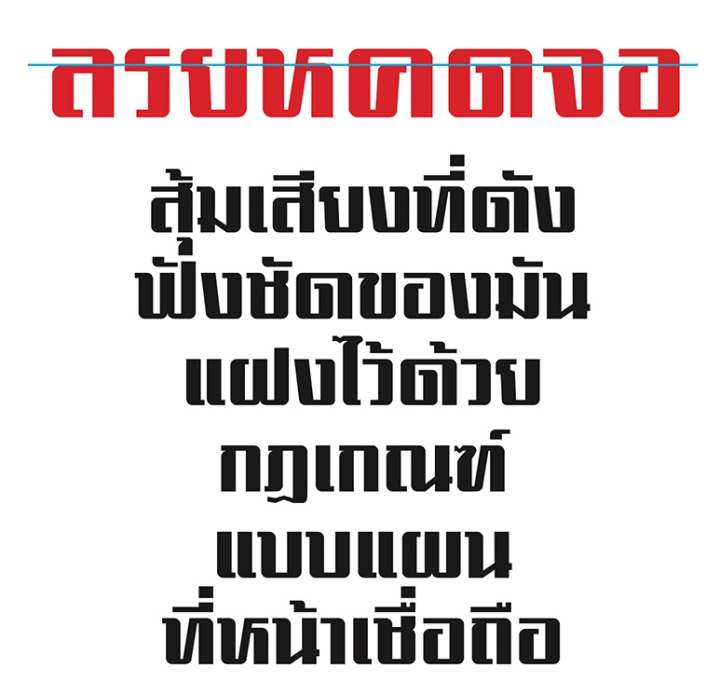
ต้องยอมรับว่าอุตสาหกรรมหนังไทยยุคก่อนเป็นที่รวมของยอดฝีมือ ทั้งช่างเขียนภาพ ช่างเขียนตัวอักษร เพราะในยุคนั้นอยากได้ภาพโปสเตอร์ขนาดใหญ่แค่ไหนต้องเขียนลูกเดียว ไม่มีงานพิมพ์ inkjet ใหญ่ขนาดห่อหุ้มตึกทั้งตึกได้อย่างปัจจุบันนี้! กล่าวได้ว่าการเกิดขึ้นของเทคโนโลยียุคดิจิทอลทำให้งานกราฟิกล้ำไปไกลมาก จนวิธีการเขียนภาพโชว์ฝีแปรง รวมทั้งตัวอักษรในโปสเตอร์กลายเป็นของทำยาก เพราะขี้เกียจทำ! ตอนนี้แค่มีไฟล์ภาพดารามาให้ มีฟอนต์ที่ถูกใจก็จบงานโปสเตอร์ได้โดยไม่ต้องถึงมือช่างเขียนขั้นเทพเหมือนแต่ก่อน. การเกิดขึ้นของหนังย้อนยุคอย่าง ‘ฟ้าทะลายโจร’ ใน พ.ศ.2543 จึงนับว่าถูกที่ถูกเวลา เพราะคนไทยยุคเก่าก็โหยหา คนยุคใหม่ก็รู้สึกแปลกตา. คนยุคกลางเก่ากลางใหม่อย่างผมจึงชอบมากเป็นพิเศษ!
แบบอักษร SR Fahtalailone โดย ‘โรจ สยามรวย’ ที่ใช้กับหนังเรื่องนี้ รวมทั้ง DB ChokeChai (DB#7) ถือเป็นงานตัวพิมพ์ย้อนยุคประเภทเขียนมือของ ‘คณะช่าง’ หนึ่งในกลุ่มยอดฝีมือผลิตงานโฆษณายุคเก่า. ในยุคสมัยเดียวกันนี้ ยังมีอักษรประดิษฐ์อีกประเภทหนึ่งที่ใช้เครื่องมือเขียนแบบง่ายๆ คือ ไม้ที ไม้ฉาก ช่วย เป็นที่นิยมใช้กันมากในวงการหนังไทย โดยพัฒนารูปแบบตามกันมา. พบได้ทั่วไปตั้งแต่ตัวพาดหัวบนโปสเตอร์ ใบปิดหนัง จนถึงโลโก้ของบริษัทสร้างหนังหลายแห่งในยุคนั้น.
สำนึกสาธารณะ
ยุคที่การเมืองกลายเป็นธุรกิจ, ยุคที่ข้าราชการกลายเป็นข้านักการเมืองและข้านักธุรกิจ, DB YangDung ถูกใช้ปลุกสำนึกสาธารณะก่อนประเทศถึงกาลล่มสลาย
ตัวเหลี่ยมหนังไทย
ชื่อคาราแสดงนำจากโปสเตอร์ ‘สันติ-วีณา’ ภาพยนตร์ 35 มม. เรื่องแรกของไทย
ตัวอย่าง Logo บริษัทสร้างภาพยนตร์ไทย (ภาพจาก ‘ร้อยปีหนังไทย’ รวบรวมโดยโคม สุขวงศ์ และสวัสดิ์ สุวรรณปักษ์)
โฆษณาชวนเชื่อ หนังสือรวมบทกวีของนักปฏิวัติชาวจีนผู้ยิ่งใหญ่ ถูกแปลเป็นภาษาไทยในยุคโฆษณาชวนเชื่อลัทธิคอมมิวนิสท์ ก่อนเหตุการณ์ 6 ตุลาคม 2519 กลับมาตีพิมพ์ใหม่ ด้วยตัวพาดหัวอย่างดัง โดยสำนักพิมพ์โลกทรรศน์
ลักษณะทั่วไปของตัวเหลี่ยมหนังไทยกลุ่มนี้คือเป็นตัวเหลี่ยม (ตามเครื่องมือหลักที่ใช้ร่าง) หัวอักษรเป็นขีดสั้นๆ ในแนวนอน (ไม่นิยมละหัวแบบหายไปเลยอย่างในปัจจุบัน) เส้นแนวตั้งมีตั้งแต่ค่อนข้างหนาจนถึงหนาทึบ, เส้นแนวนอนค่อนข้างบาง. รายละเอียดที่น่าสนใจ คือ สันของมุมฉาก ที่เกิดจากเส้นนอนทำมุมกับเส้นตั้งนั้นจะถูกลบมุมให้โค้งมน (ส่วนพับในคงปล่อยให้เป็นฉากอยู่) การลบมุมฉากดังกล่าวนี้ เป็นประโยชน์มากต่อตัวเหลี่ยมกลุ่มนี้ เพราะทำให้เราสังเกตทิศทางของหัวได้ง่าย เราจึงเห็นความแตกต่างระหว่าง ผ กับ พ ได้ชัดเจน (แม้ว่าเส้นกลางตัว ผ ชุดนี้จะนิยมเขียนสูงเสมอเส้นหลังเหมือนตัว พ ก็ตาม). การลบมุมฉากเฉพาะสันที่ว่ามานี้ นอกจากจะเป็นการแสดงออกถึงเชิงช่าง เป็นการลดความกระด้างแล้ว ยังมีส่วนช่วยให้อักษรทั้งชุดอ่านง่ายมากขึ้น นั่นเพราะหัวถือเป็นอัตลักษณ์ที่สำคัญของอักษรไทย และมีอักษรไทยหลายคู่ที่ดูต่างกันได้ โดยอาศัยทิศทางการหันหัว ที่เห็นชัดว่าต่างกันนั่นเอง.
จุดเด่นอีกประการหนึ่งของตัวเหลี่ยมหนังไทยกลุ่มนี้ คือ ตัวอักษรมีขนาดความกว้างที่แตกต่างกันอย่างเห็นได้ชัด แยกเป็น 3 กลุ่ม คือ 1) กลุ่มตัวที่มีความกว้างปรกติ ซึ่งเป็นส่วนใหญ่ ได้แก่ ก, บ, ม, น, อ เป็นต้น 2) กลุ่มที่กว้างมาก ได้แก่ ค-ด, ผ-พ (ล, ส มีทั้งที่ตัวกว้างและตัวปรกติ) และ 3) กลุ่มที่ตัวแคบมาก เช่น ร, ว. ขนาดที่แตกต่างกันมากนี้ถือเป็นอิสรภาพของอักษรประเภทที่เขียนประดิษฐ์ขึ้นเอง. ช่างเขียนยุคนั้นมีอิสระที่จะเขียนสระอิ, อี, อึ, อื กว้างเท่ากับพยัญชนะตัวไหนก็ได้ที่มันกำกับอยู่! ต่างจากฟอนต์ไทยส่วนใหญ่ของยุค PostScript (รวมทั้งฟอนต์ OpenType ที่ย้ายตัวพิมพ์จาก PostScript มาโดยไม่ได้พัฒนาต่อ) ยังคงมีชุดสระบนเพียง 2 ชุดเท่านั้น คือชุดสำหรับตัวทั่วๆ ไป กับชุดสำหรับ ป, ฝ, ฟ ที่ต้องเบื้องหน้าเพื่อหลบหาง หรือยกสูงให้ลอยพ้นหาง.
สำนึกแห่งศรัทธา ยิ่งประเทศสับสน! ประชาชนยิ่งรักในหลวง พาดหัว 'SMEs Today เล่มที่ 62 ประจำเดือนธันวาคม 2550 โดยมนตรี จันทรศิริ เลือก DB YangDung ปลุกสำนึกแห่งศรัทธา ต่อศูนย์รวมจิตใจชนในชาติ.
การที่ตัวเหลี่ยมหนังไทยกลุ่มนี้ มีสุ้มเสียงดังฟังชัด สั่งใจคนอ่านได้ เกิดจากการเน้นเส้นตั้งให้หนาเป็นพิเศษ และใช้เส้นนอนบางเพื่อเก็บรายละเอียดสำคัญ. เราจะไม่สังเกตเห็นเส้นแนวเฉียงมากนักในตัวเหลี่ยมกลุ่มนี้ เพราะแม้จะมีก็ถูกจัดให้มีความชันสูง (เช่นตัว ง, จ) หรือไม่ก็เห็นแค่เส้นสั้นๆ อยู่ต่ำติดเส้นฐาน (เช่น น, ม) ทำให้ดูไม่เด่นชัดนัก.
ขมวดม้วนของ น ที่พบในบางชุดจะไม่มีเส้นเฉียงเลย ช่างเขียนใช้วิธีต่อเส้นหลังให้ยาวตัดฉากทับกับเส้นล่างที่ลากเสมอเส้นฐานเลยแนวเส้นหลังเล็กน้อย. เส้นคอของตัว ค จะเอนไปข้างหน้าเล็กน้อย ทำให้ดูต่างจาก ด ที่มีคอตั้งตรง อวดให้เห็นหัวที่หันฉากไปข้างหน้าได้ชัดๆ. คอตัว จ เป็นลักษณะเดียวกันกับ ค. ส่วนตัว ง นิยมเขียนให้หางหักเฉียงขึ้นไปจนเสมอระดับหัว.
ตัวที่ผมเห็นว่าน่าพูดถึงเป็นพิเศษนั้นคือตัว ย ซึ่งถือเป็นไม้เด็ดของชุดตัวเหลี่ยมหนังไทยเลยทีเดียว สังเกตให้ดี เส้นหน้าของมันมีแต่หยักเข้า ไม่ยักมีการหยักออก! ลักษณะการเขียนทำนองนี้ไม่ได้เกิดขึ้นลอยๆ มันมีรากที่มาจากตัวเขียนบนใบลานยุคโบราณของไทย. การใช้วัตถุปลายแหลมเขียนหยักเข้าออกในแนวนอนนั้นทำได้ยากบนใบลานซึ่งมีร่องใบขนานเป็นทางตามแนวนอน จึงมักนิยมเขียนแค่หยักเข้า แล้วขีดลงมาเส้นฐานแทน (ย้อนดูบทความ DB Yam ตัวพิมพ์ ยุคแรกที่ได้รับอิทธิพลจากตัวเขียน) ‘ยักษ์เก่า‘ ถูกนำมาปรับโฉมใหม่เล็กน้อยในชุดตัวเหลี่ยมหนังไทย โดยแทนที่จะหยักเข้าแล้วขีดลงขนานกับเส้นหลังกลับเขียนลงแบบสอบเข้าหา เส้นหลังเล็กน้อย เกิดเป็นเส้นเฉียงล้อกับตัวอื่นๆ. ย จึงกลายเป็นตัวเด่นของกลุ่ม ทั้งอ่านง่าย สวยงาม และจำง่าย ครบเครื่องจริงๆ. ใครเป็นคนเขียน ย แบบนี้ เป็นคนแรกจึงเป็นเรื่องที่น่าสืบค้น (ก่อนหลักฐานที่หลงเหลืออยู่จะเสื่อมสูญ) เพื่อการเชิดชูซูฮก!
ในการอนุรักษ์เป็นฟอนต์ดิจิทอล ผมตั้งชื่ออักษรเหลี่ยมหนังไทยเสียใหม่ว่า ‘อย่างดัง’ ให้สมกับบุคลิกที่แสดงออกถึง ความยิ่งใหญ่แห่งยุคสมัยของมัน. DB YangDung (DB#3) เกิดขึ้นในช่วงที่เมืองไทยยังใช้ฟอนต์แบบ PostScript กับคอมพิวเตอร์เก่าอยู่มาก จึงต้องทำอย่างดังเป็นฟอนต์ทั้งแบบ PostScript และ OpenType (DB YangDung และ DB YangDung X ตามลำดับ)
เพราะฟอนต์อย่างดังแบบ PostScript ทำจาก Fontographer ซึ่งไม่มี feature ที่เรียกว่า Ligature ให้ใช้ จึงเป็นอุปสรรคที่จะรักษาเอกลักษณ์ชุดสระบนที่เปลี่ยนความกว้างไปตามพยัญชนะที่มันกำกับอยู่ ดังที่ผมได้กล่าวไปแล้วได้, จึงต้องจำยอมทำตัว ร, ว ให้กว้างกว่าต้นแบบ เพื่อใช้ชุดสระบนร่วมกับตัวปรกติและตัวกว้างได้. ส่วนฟอนต์อย่างดังในชุด ที่เป็น OpenType เราสามารถย้อนยุคกลับไปรักษาความจิ๊กโก๋เดิมๆ ได้ เพราะ Ligature ที่มีใน FontLab ทำให้สามารถเขียนคำสั่งเลือกสระขนาดเหมาะสมกับความกว้างของพยัญชนะได้นั่นเอง. ใครอ่านถึงตรงนี้แล้วลองจินตนาการถามตัวเองดูซิว่า ผมควรทำ DB YangDung ให้มีชุดสระอิ, อี, อึ, อื ความกว้างแตกต่างกันซักกี่ชุคถึงจะพอ?...
คำตอบคือ 1) ชุดสำหรับตัวกว้างปรกติ 2) ชุดสำหรับตัวกว้างเป็นพิเศษ 3) ชุดสำหรับตัวแคบเป็นพิเศษ 4) ชุดตัวกว้างปรกติที่มีหางตั้ง คือ ป และ 5) ชุดตัวกว้างพิเศษที่มีหางตั้ง คือ ฝ, ฟ เบ็ดเสร็จรวม 5 ชุดพอดี! บางคนอาจมีคำถามว่า ทำไมพวกกว้างแต่กำเนิดโครงสร้าง 4 ตัวอย่าง ฌ, ญ, ฒ ณ ผมจึงไม่จัดชุดพิเศษชุดที่ 6 ให้? คำตอบคือ ตัวมันกว้างมาก มากกว่าพวก ด, พ ฯลฯ เสียอีก เมื่อลองใช้ชุดสระอีของตัวปรกติพิมพ์ ณี ดูพบว่า แม้จะสั้นแต่ยอมรับได้ ด้วยความเคยชิน เนื่องจาก ณ เป็นการรวม 2 ร่าง ระหว่าง ถ และ น จึงดูเสมือนสระมันอยู่บนตัวหลังคือ น พออนุโลมได้. เมื่อลองเอาสระอีของชุดตัวกว้างไปลองวางกำกับ ณ ดูกลับพบว่ามันดูไม่เรียบร้อย เพราะปลายสระแค่ยาวอีกหน่อย ก็จะกว้างครอบคลุมตัว ณ พอดี. ครั้นต่อให้ยาวเสมอหน้าตัว ณ กลับพบว่ามันยาวรุ่มร่ามเกินงามไปเสียอีก! เลยจบลงที่ 5 ชุดครับ.
สำหรับชุดอักษรโรมันของ DB YangDung รวมทั้งเลขอารบิก ถูกออกแบบขึ้นใหม่ทั้งหมดโดยยึดหลักการของช่างเขียนชั้นครูที่ตกทอดมาถึงเรา. ตัวพิมพ์เล็กหลายตัว เช่น c, e, s และเลข 2, 3, 5 จะปล่อยเส้นบนเส้นล่างให้เหยียดตรงตามแนวนอนเหมือนเส้นบนที่พบใน จ, ล ของกลุ่มตัวเหลี่ยมหนังไทย จึงให้เสียงใกล้เคียงชุดอักษรไทยมาก.
ถึงแม้ ตัวพิมพ์ จะเป็นเพียง ‘เสียงชนิดเงียบ’ ก็ตาม ‘ความดัง’ ของ DB YangDung มันยังคงก้องกังวานนานเกินกึ่งศตวรรษ และยังไม่มีทีท่าจะเงียบลงได้ด้วยซ้ำ.
เป็น ‘ความดัง’ ที่ยั้งไม่อยู่อย่างแท้จริง.